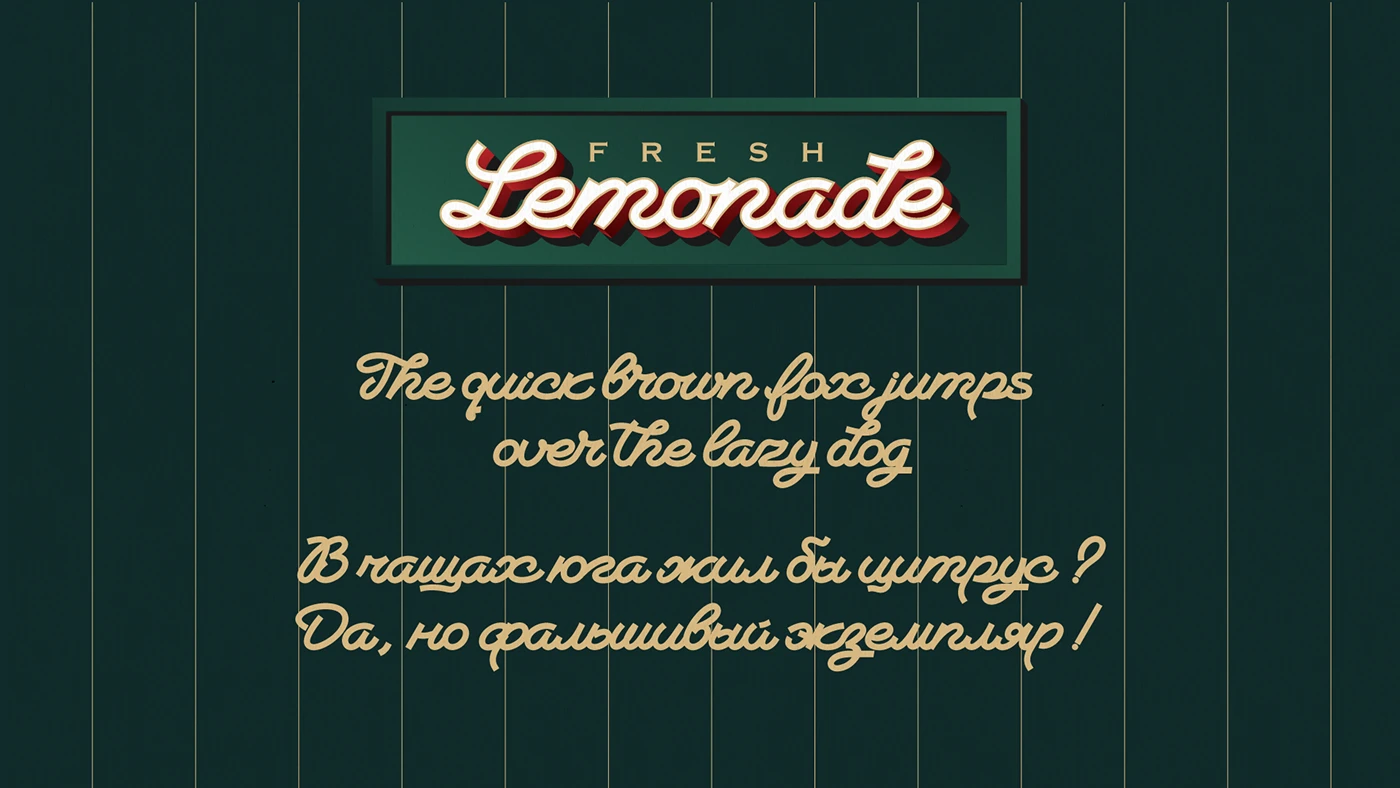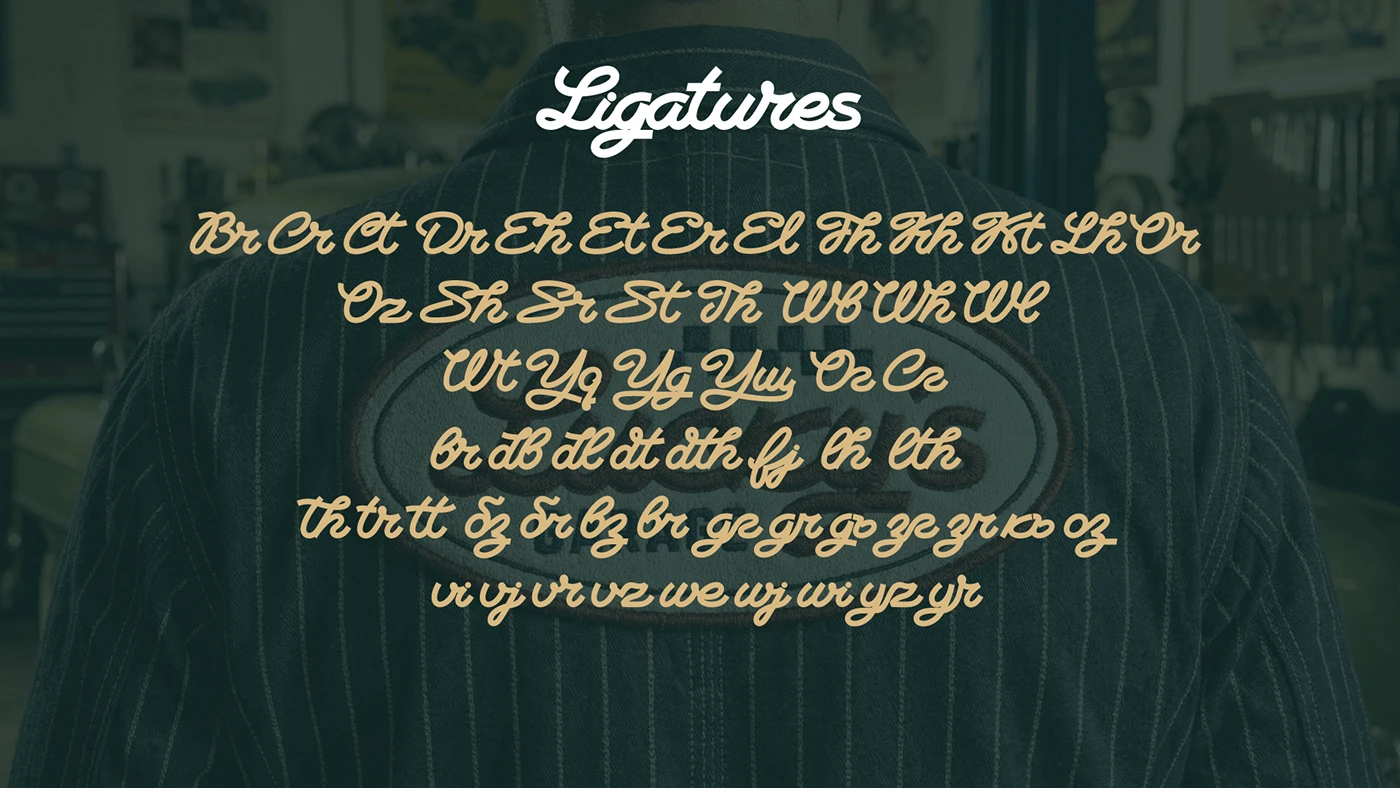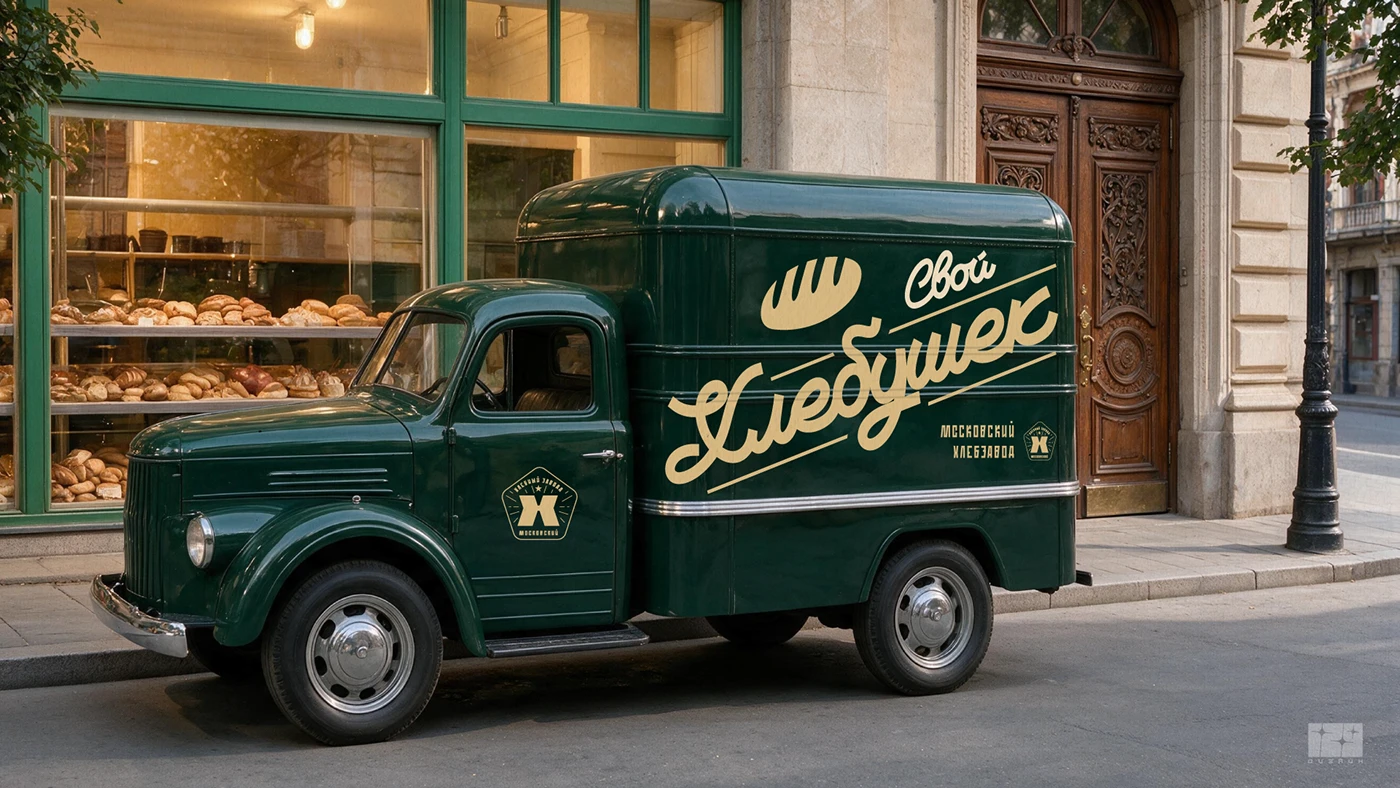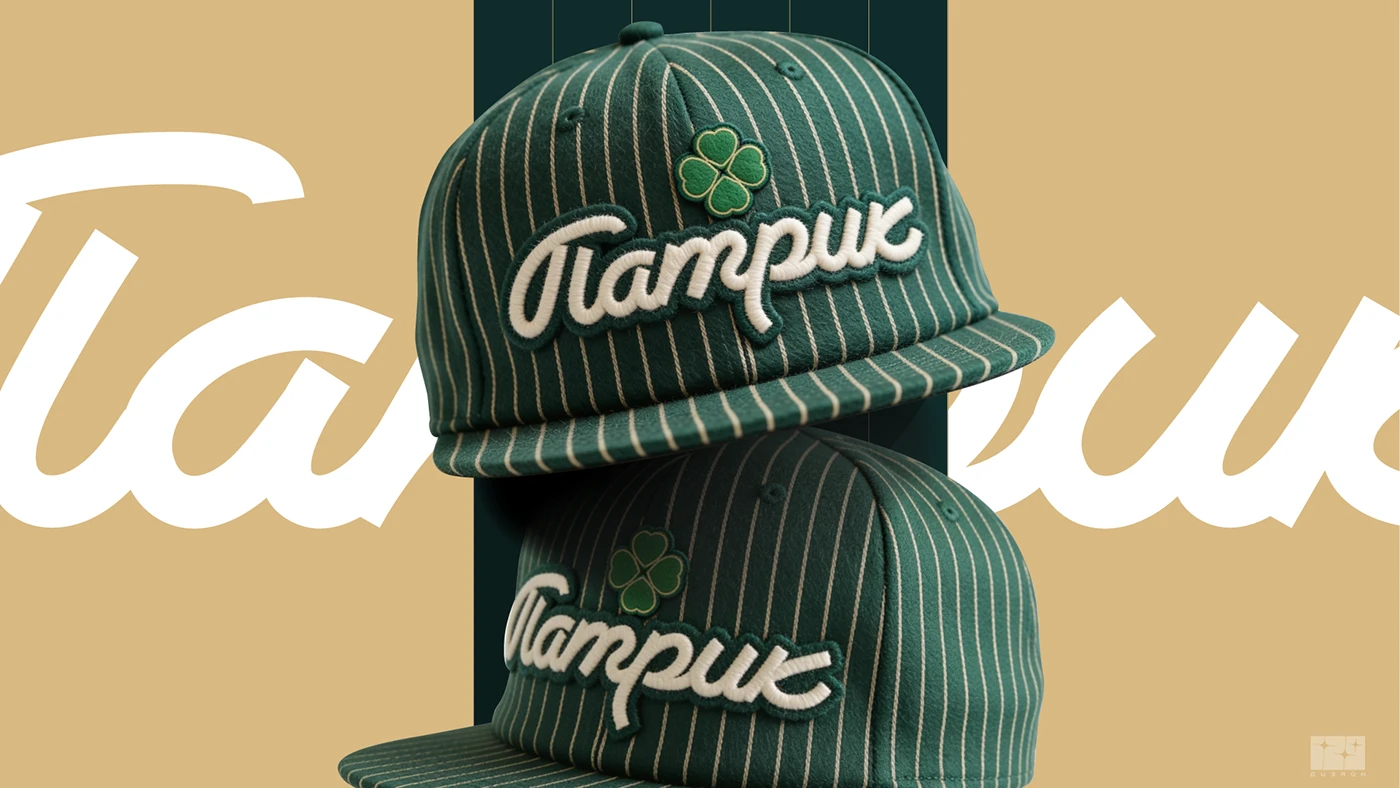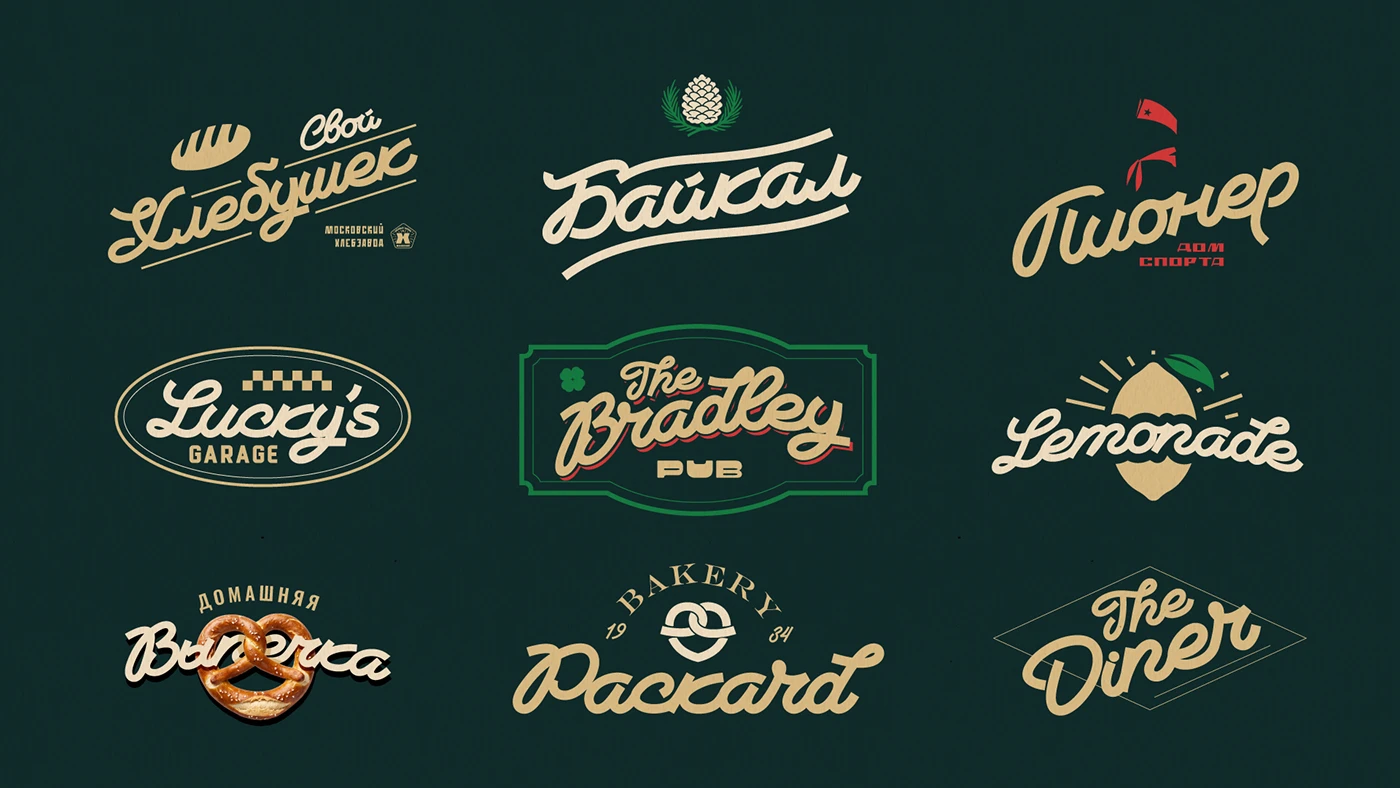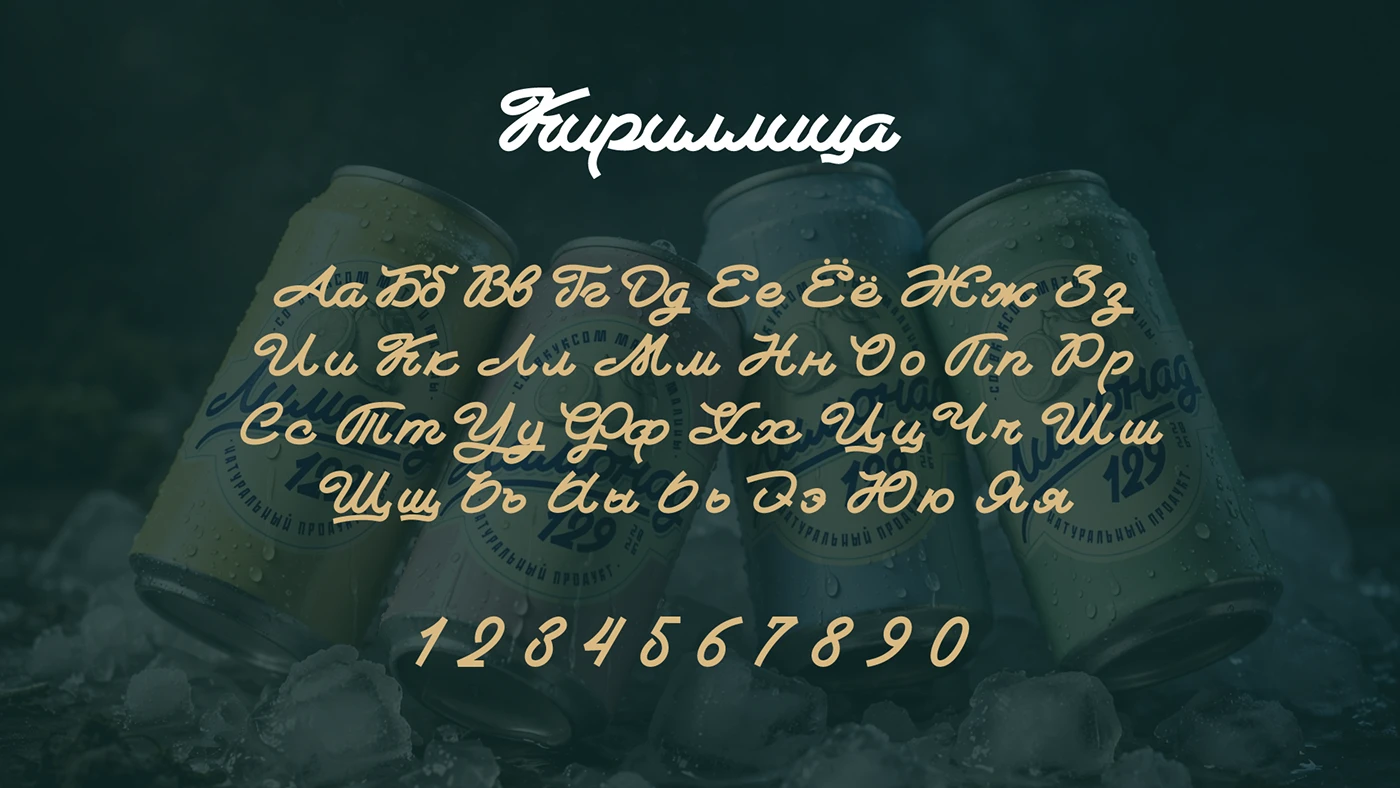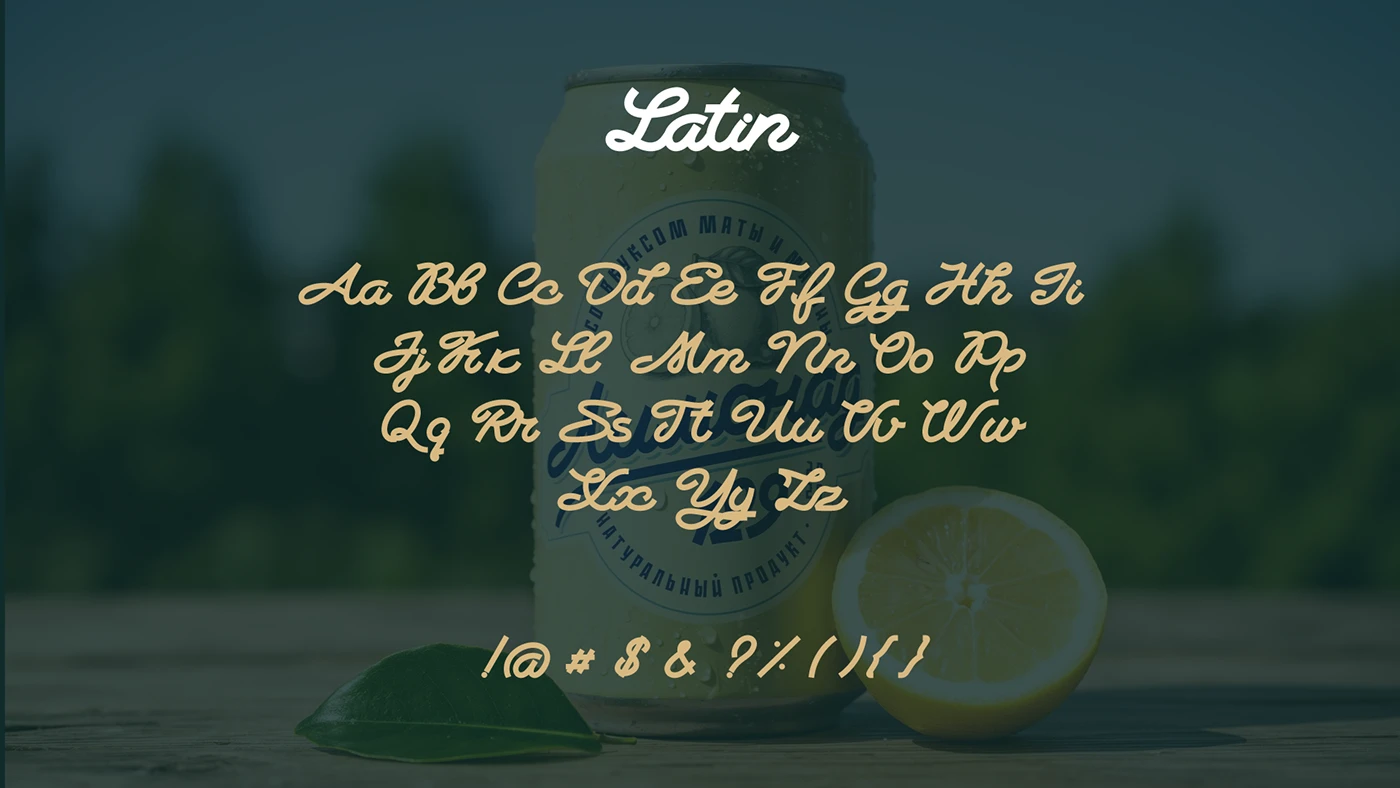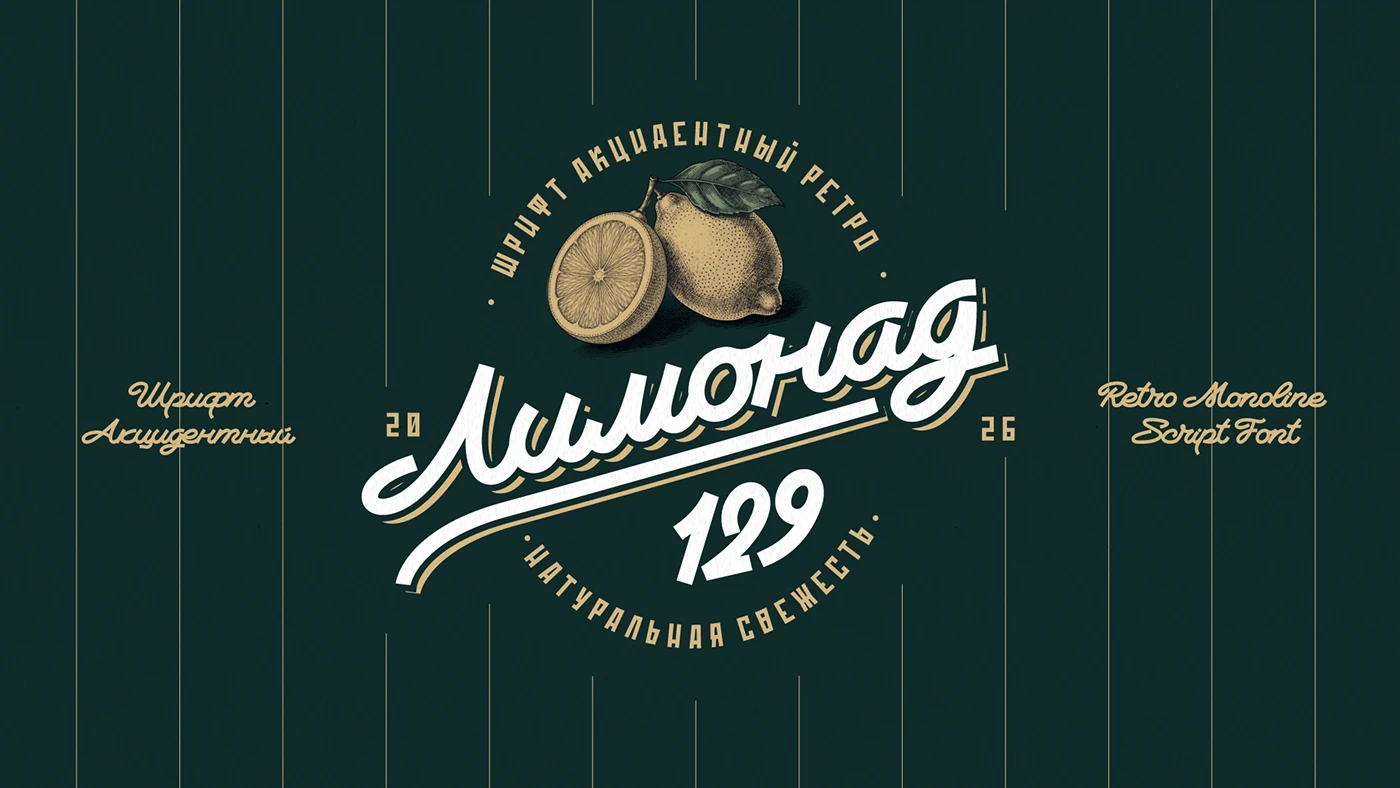
Моноширинный шрифт с элементами ретро, вдохновленный рукописными вывесками магазинов 40-х годов, идеально подходит для создания логотипов и коротких текстовых надписей. Его уникальные особенности включают в себя буквы разной ширины и наклона, а также отсутствие узлов, что отражает авторский подход и концепцию.
Автор: Vadim Bashlakov